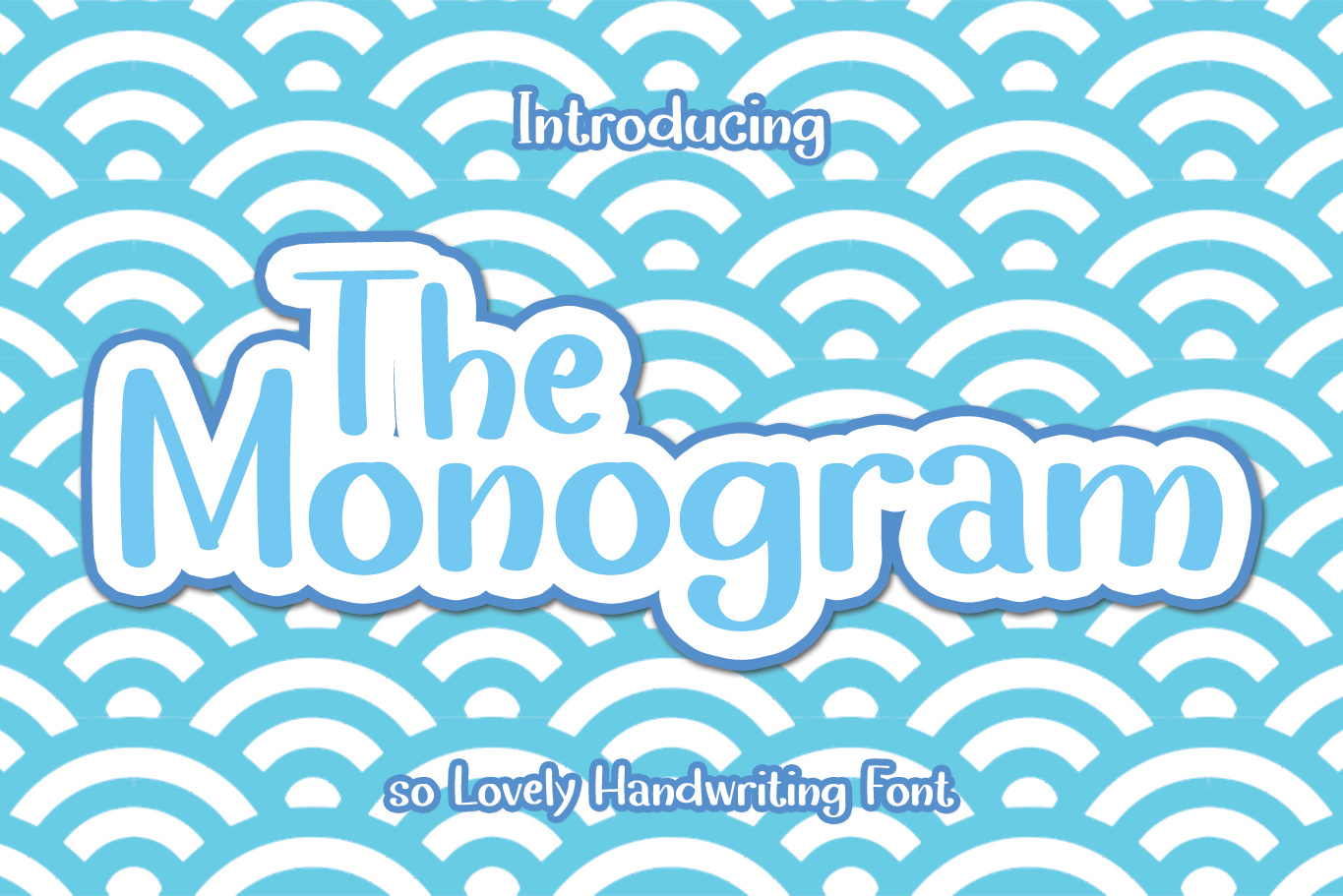
The Monogram Font – Download Grátis
Esta é uma fonte script divertida e animada. Independentemente do tema, esta fonte será um incrível ativo para sua biblioteca de fontes, pois tem potencial para revolucionar qualquer criação. A The Monogram Font é perfeita para aqueles que buscam algo casual e versátil, mas com uma pitada divertida para tornar seu trabalho ainda mais atraente. Seja você um designer gráfico, uma pessoa de mídia social ou um criador de conteúdo online, esta fonte vai adicionar um toque especial à sua próxima obra. Ela é perfeita para criar headlines memoráveis, estilos bem-humorados ou até mesmo simples mensagens que chamem a atenção. Não importa o tipo de projeto que você esteja lidando, The Monogram Font está aqui para torná-lo ainda mais impressionante e único.